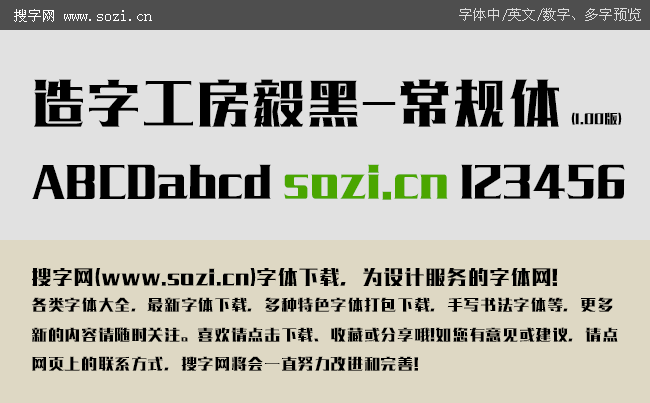
造字工房毅黑常規(guī)體
搜字網(wǎng)給大家提供一款很有力的造字工房毅黑常規(guī)體字體下載。造字工房毅黑體整體風(fēng)格粗曠厚重、主次筆畫處理極其鮮明、結(jié)構(gòu)方正均衡,細(xì)膩出彩的筆畫特點(diǎn)讓字形整體更加剛毅,充滿力量,灑脫而靈動,且具有極強(qiáng)的時(shí)尚感。此款字體適用于文字標(biāo)題、廣告設(shè)計(jì)、企業(yè)宣傳等視覺環(huán)境,有著極強(qiáng)的應(yīng)用空間。